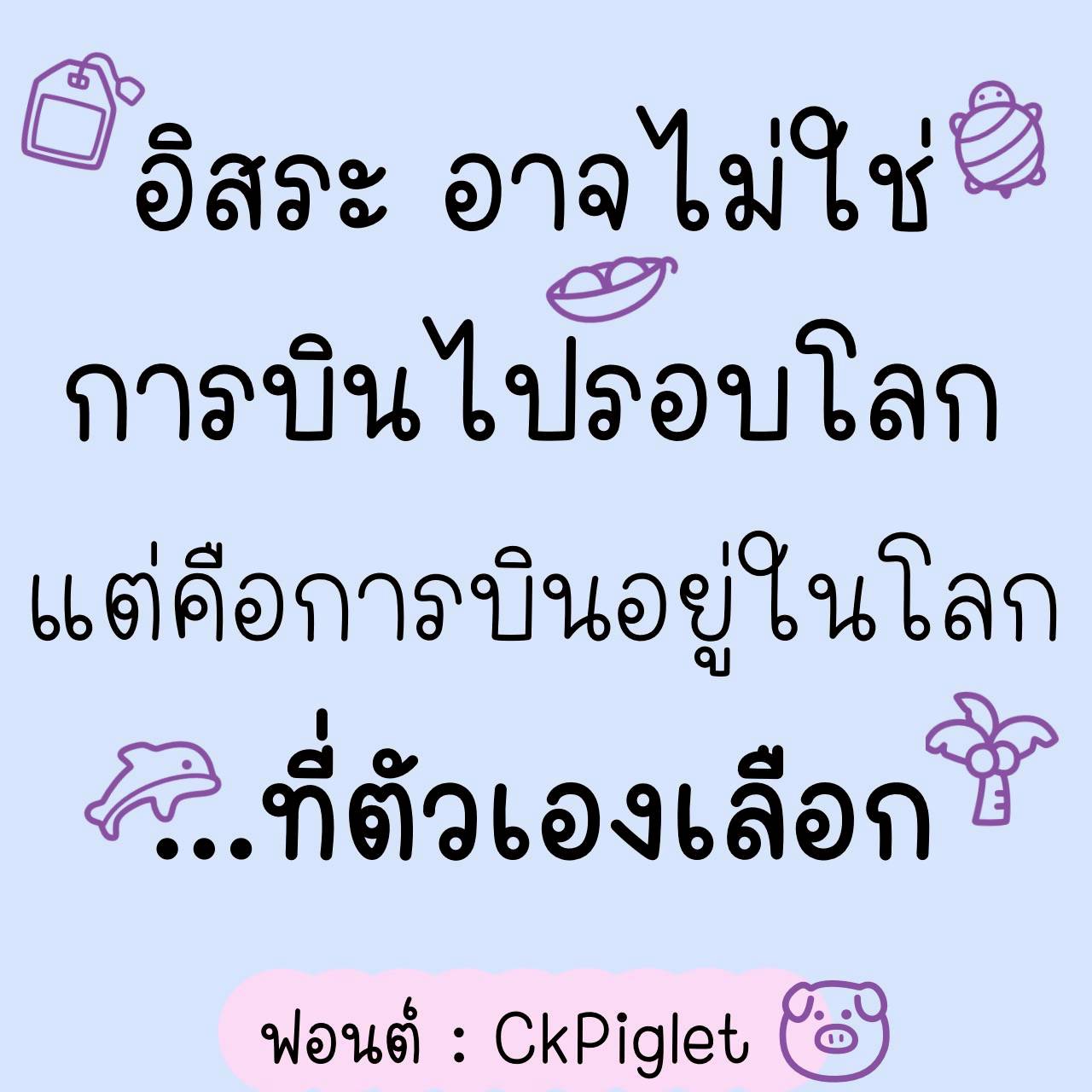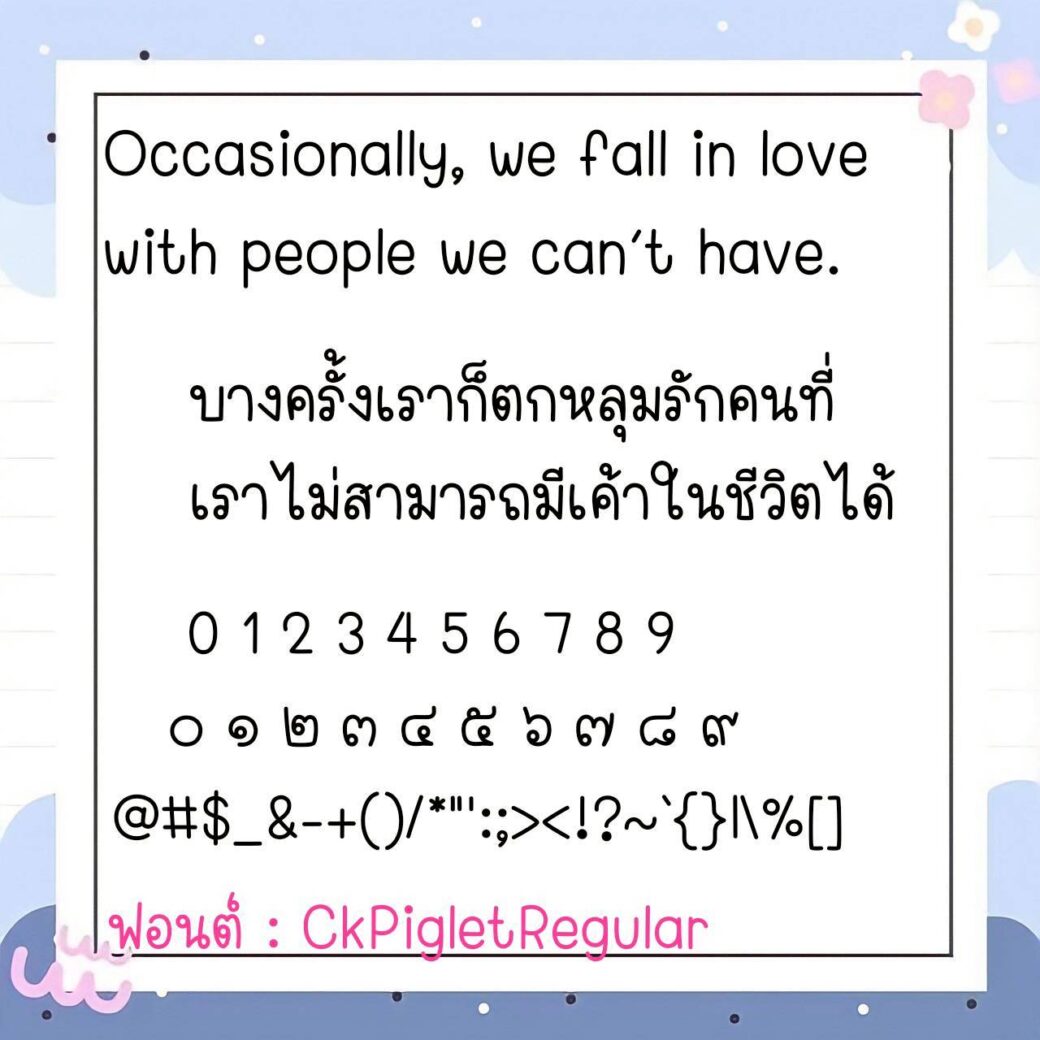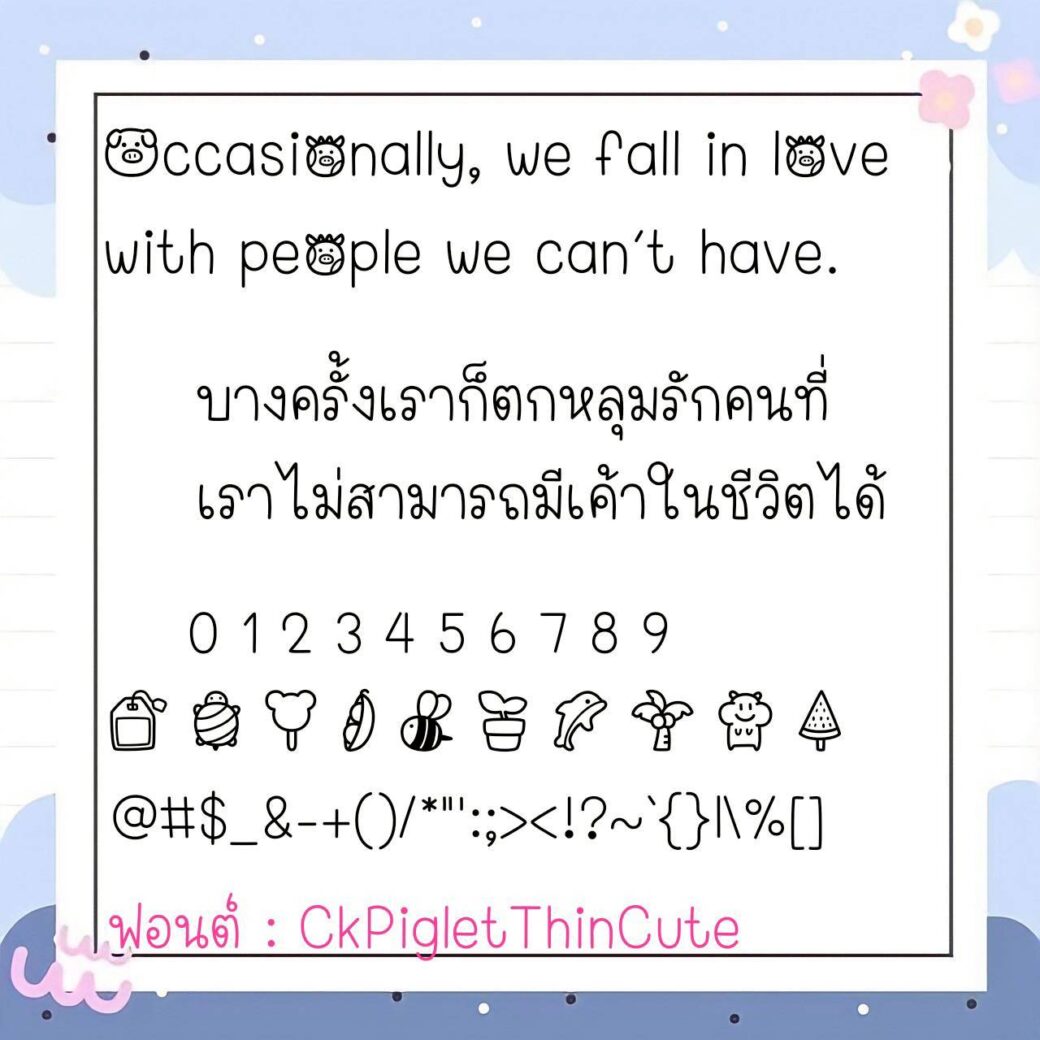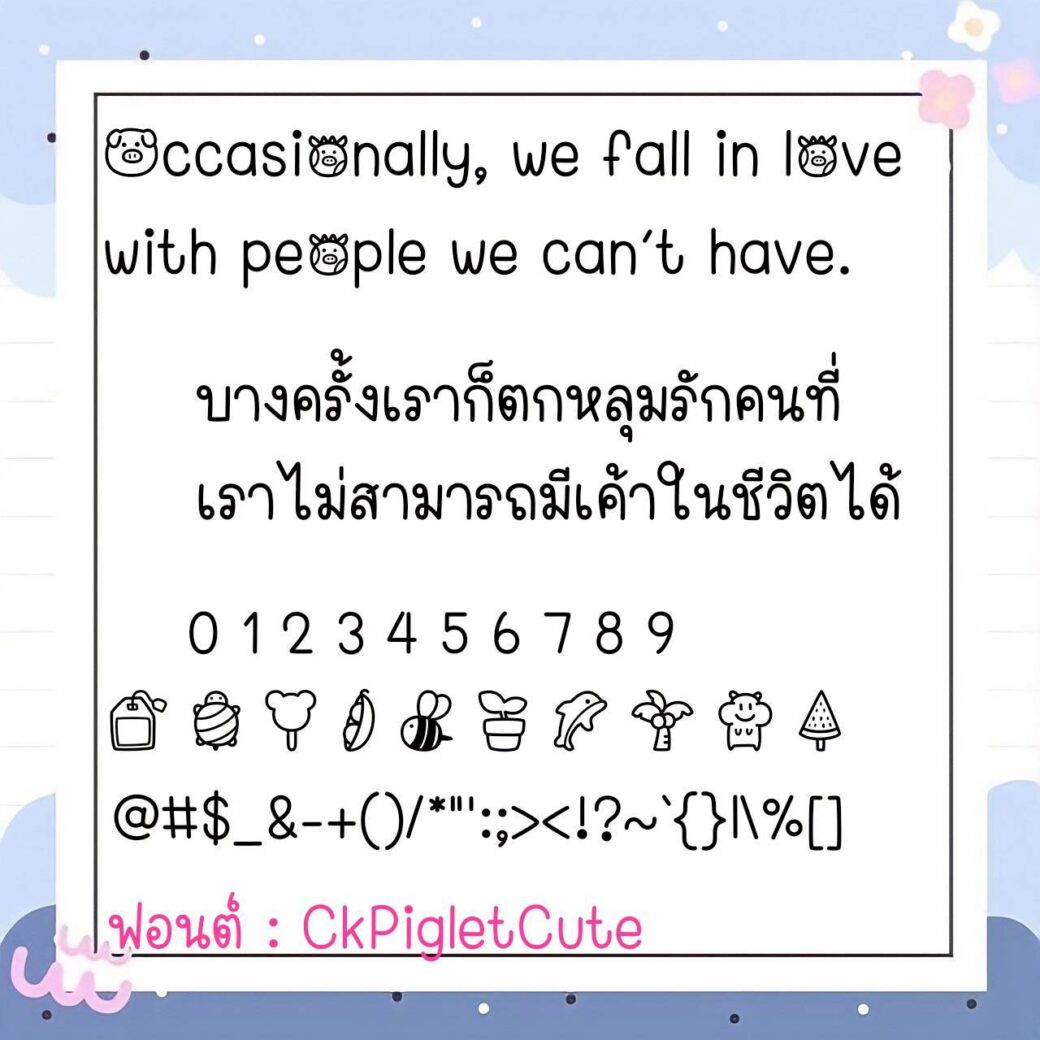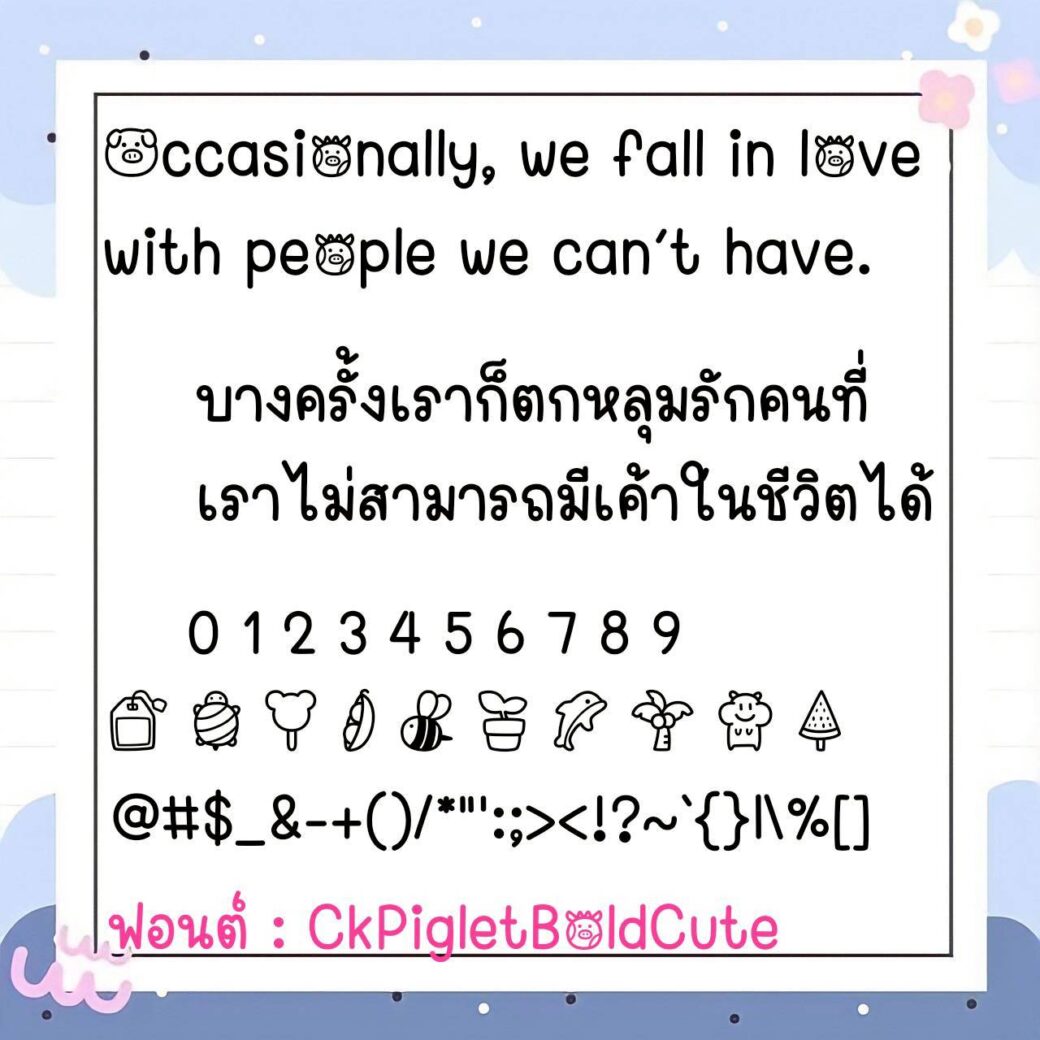
Font CkPiglet
ชื่อสินค้า : Font CkPiglet 💙
🔸 ฟอนต์ลายมือแนววัยรุ่น ดูมีความน่ารักแบบวัยรุ่นในตัว แต่ยังเน้นให้อ่านง่าย ดูสบายตาเช่นเดิม และยังมีไฟล์อิโมจิน่ารักๆ ที่ใช้แทนเลขไทยให้ด้วยค่ะ 🥰💙
🔹 A handwritten font for teenagers that looks cute and youthful, but still emphasizes easy reading and is easy on the eyes. There are also cute emoji files that can be used instead of Thai numerals. 🥰💙